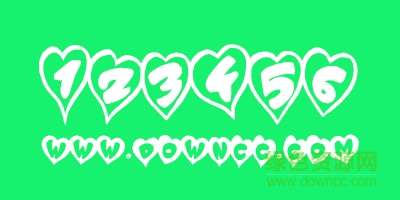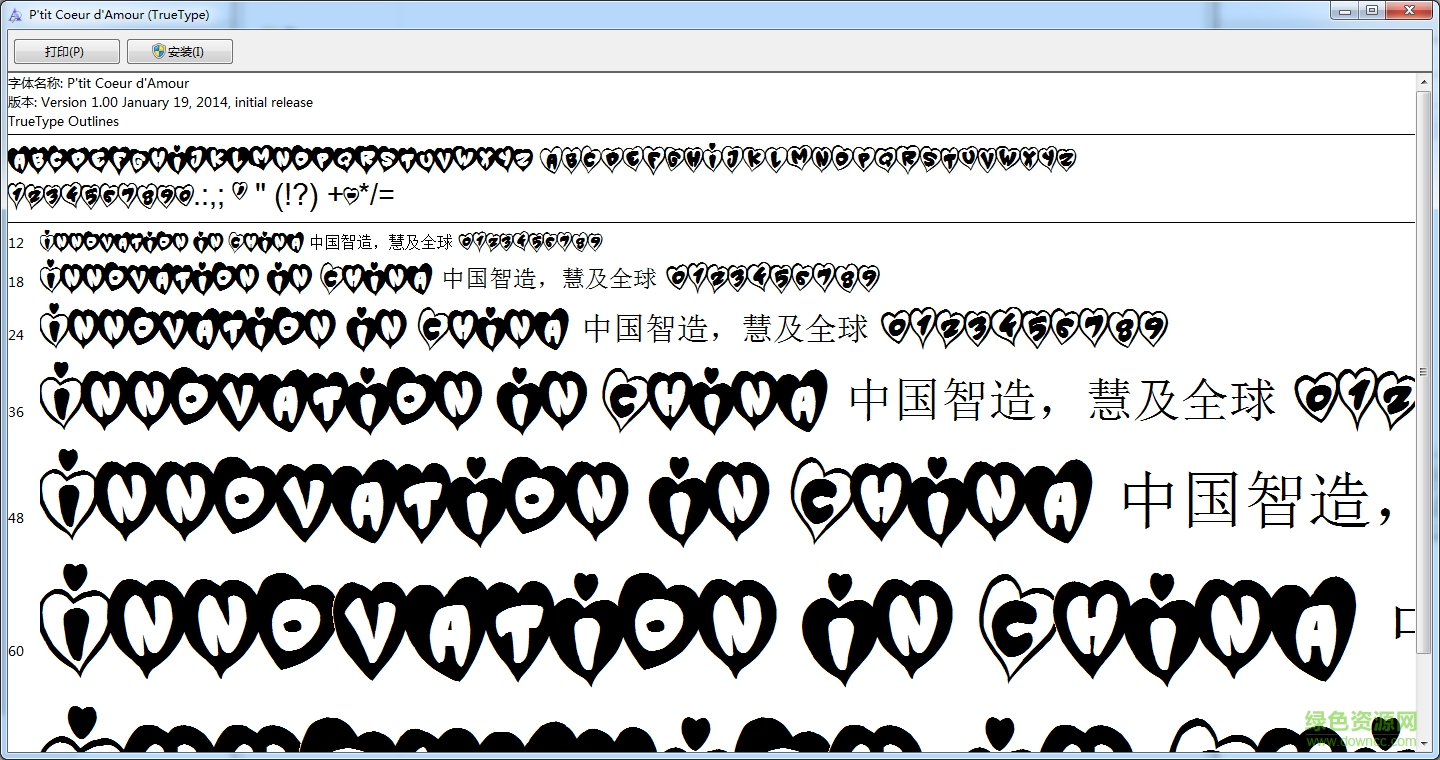
可愛心形英文字體
心形英文字體書寫英文字母時特別的美觀。呆板的英文字母瞬間變得有朝氣和活力!不過輸入文字時,倒是沒啥效果顯示的!喜歡的朋友歡迎下載。
可愛心形英文字體
心型英文字體是一款比較呆萌的字體。字體外面被桃心包圍,非常具備藝術(shù)感,設計行業(yè)的朋友可以來綠色資源網(wǎng)拿走使用喲!